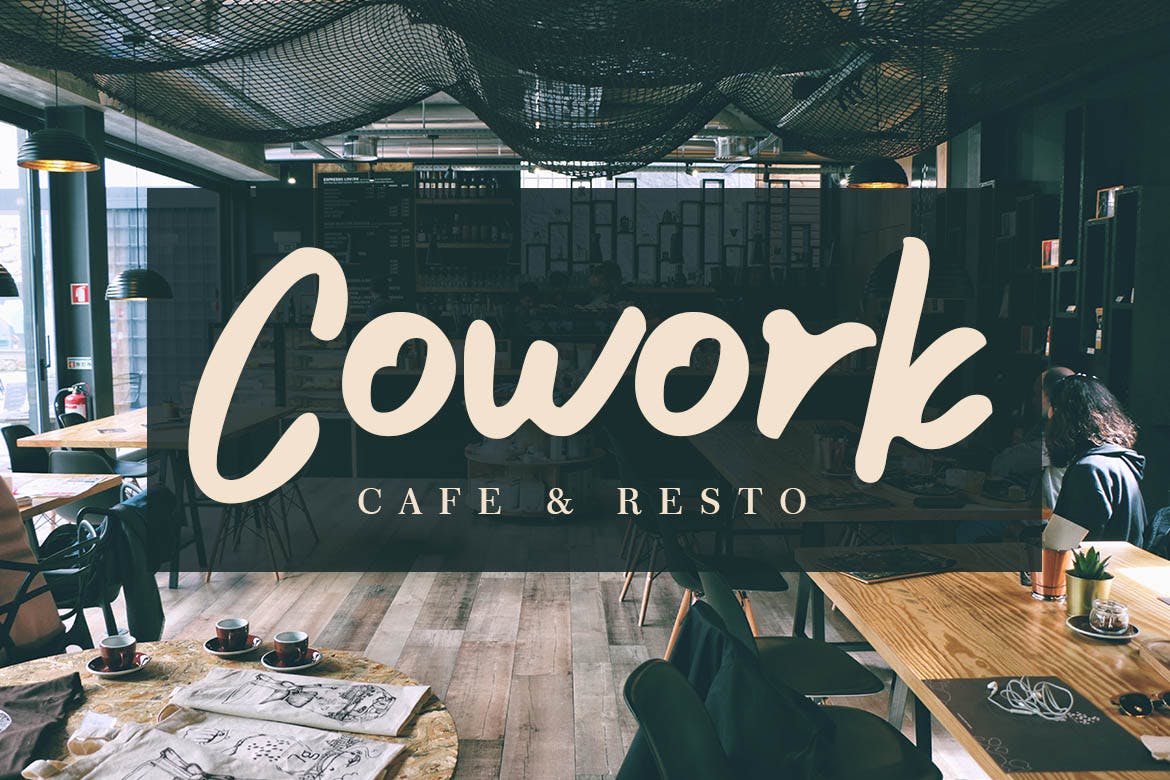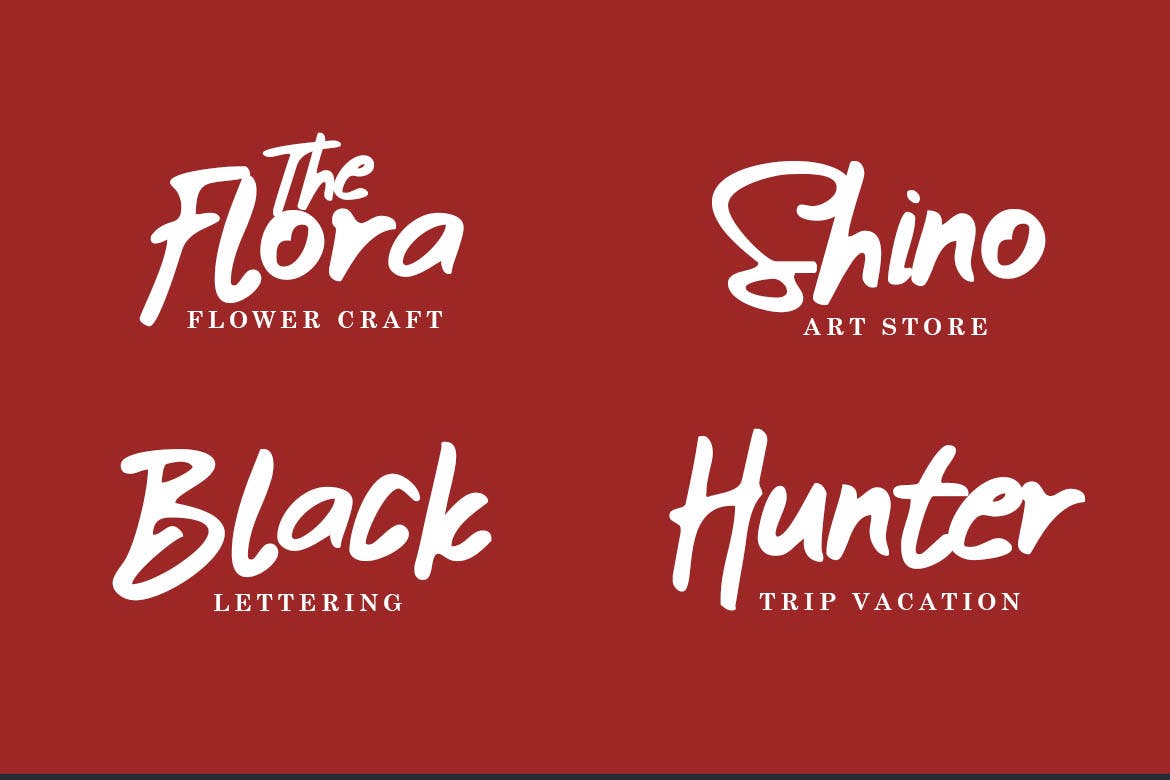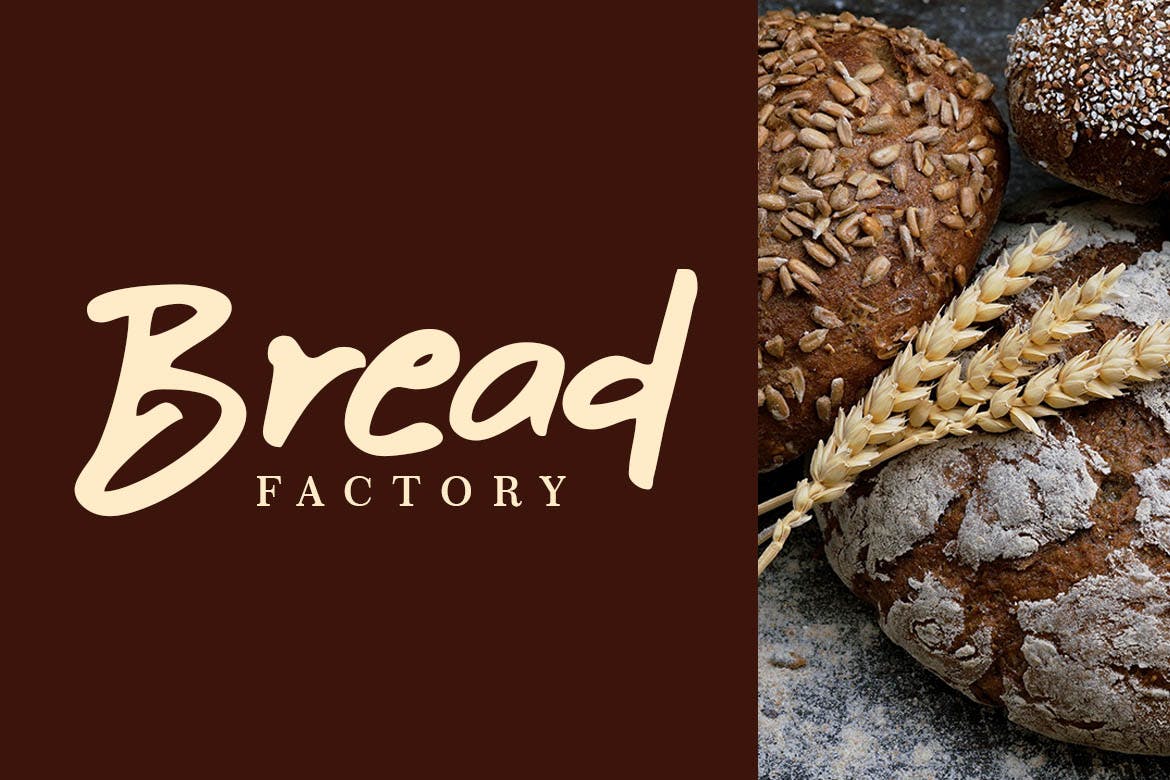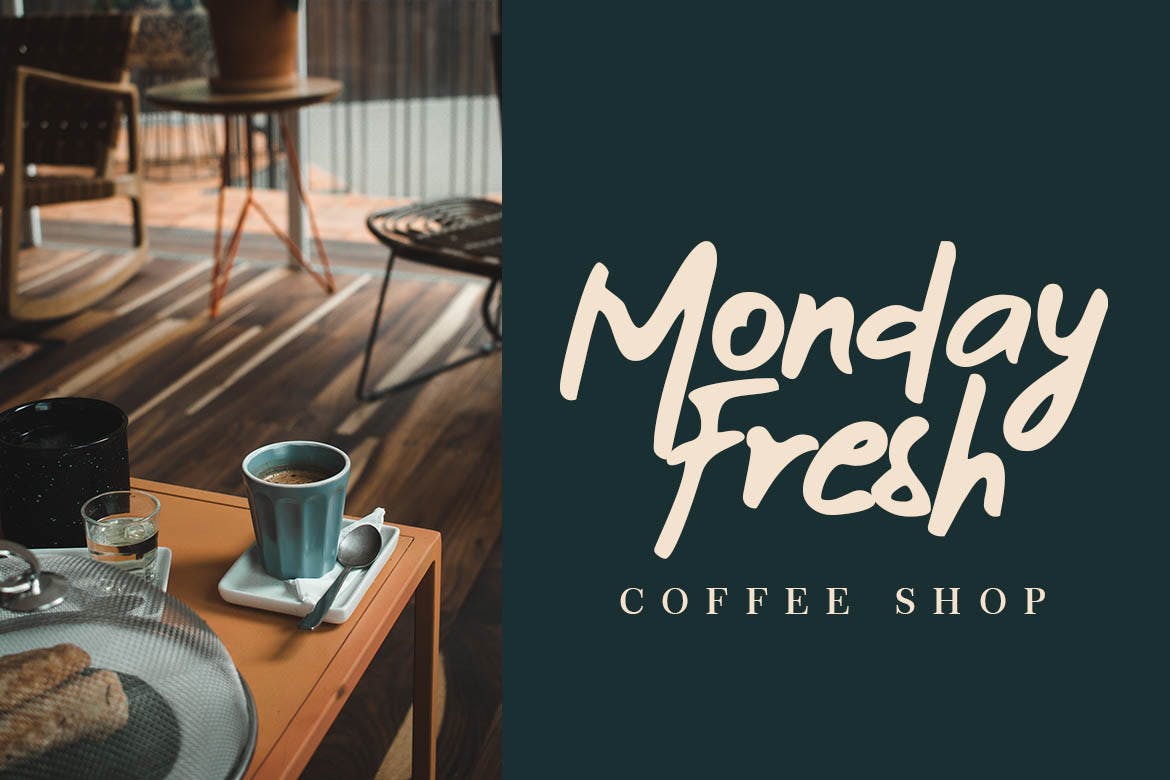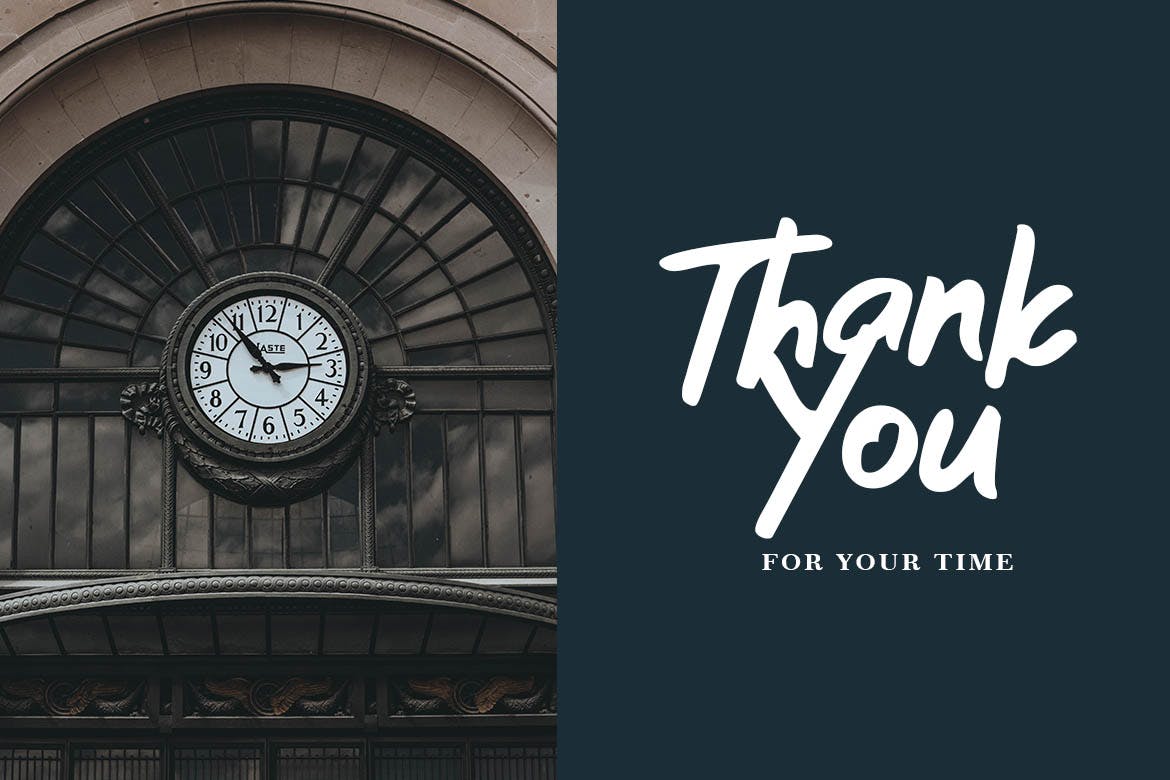
Brown Choco Logo Font
فونت لوگو براون چاکو، انتخابی منحصر به فرد برای طراحی‌های شما.
فونت لوگو براون چاکو (Brown Choco) یک فونت منحصر به فرد برای طراحی لوگو است. این فونت برای طراحی لوگو، نقل قول‌ها، پوسترها، نوشتار بازیگوش، لباس و هر پروژه طراحی دیگری مناسب است.